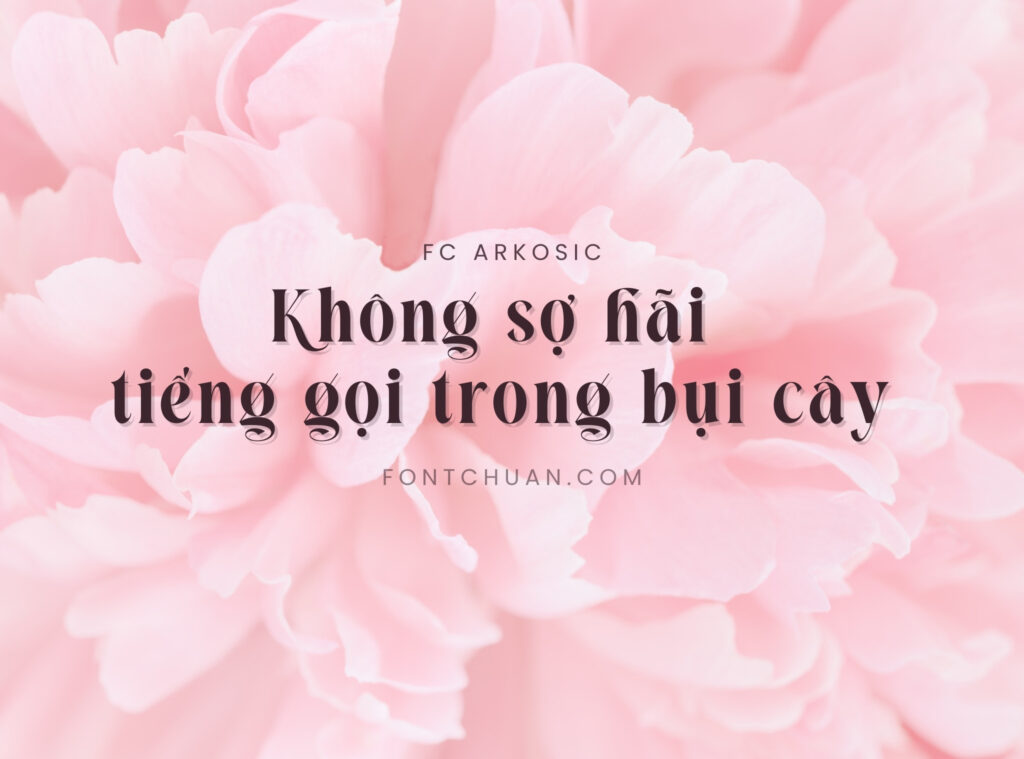
Arkosic là một font chữ serif thanh lịch, được thiết kế để mang lại trải nghiệm đọc thoải mái cho các văn bản dài. Lấy cảm hứng từ tác phẩm của họa sĩ Diego Velázquez và nghệ thuật Baroque Tây Ban Nha, Arkosic ngoài các ký tự đơn truyền thống còn có các ký tự ghép độc đáo (View Glyph để xem), kết hợp giữa vẻ đẹp cổ điển và hiện đại, tạo nên sự tinh tế và sang trọng cho các dự án thiết kế. Với tính linh hoạt cao, Arkosic cũng có thể được sử dụng như một Font Lễ hội để trang trí các thiệp mời, poster, banner sự kiện hay ấn phẩm đặc biệt, mang đến không khí vui tươi và ấn tượng.
Với cấu trúc chữ cân đối, độ dày vừa phải và các đường nét mềm mại, Arkosic phù hợp cho các thiết kế logo, tiêu đề, thương hiệu và các ấn phẩm biên tập khác. Đặc biệt, font này thích hợp cho các ngành nghề như quảng cáo, thiết kế thiệp cưới và lĩnh vực xuất bản, nơi cần sự kết hợp giữa thẩm mỹ cổ điển và chức năng truyền tải thông điệp.